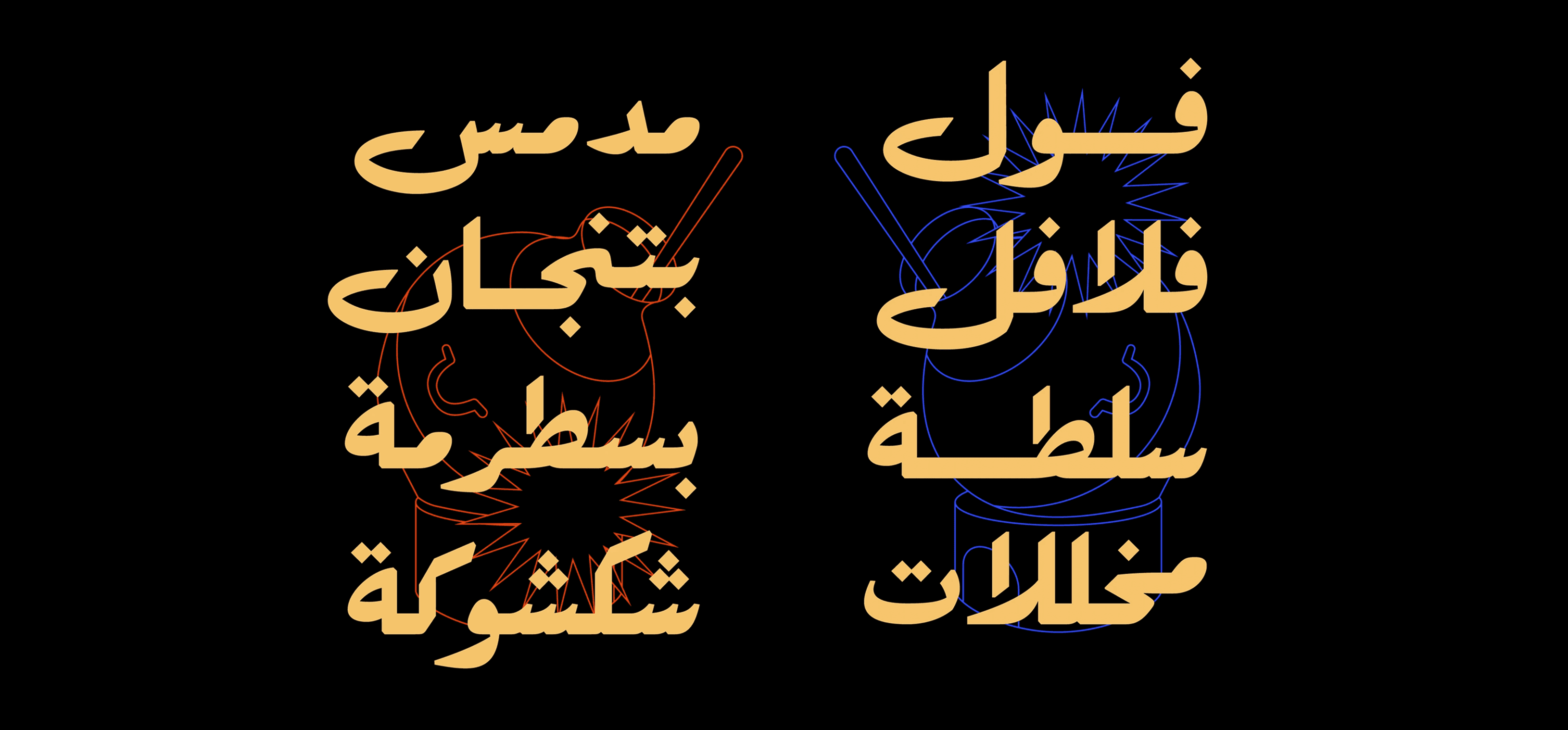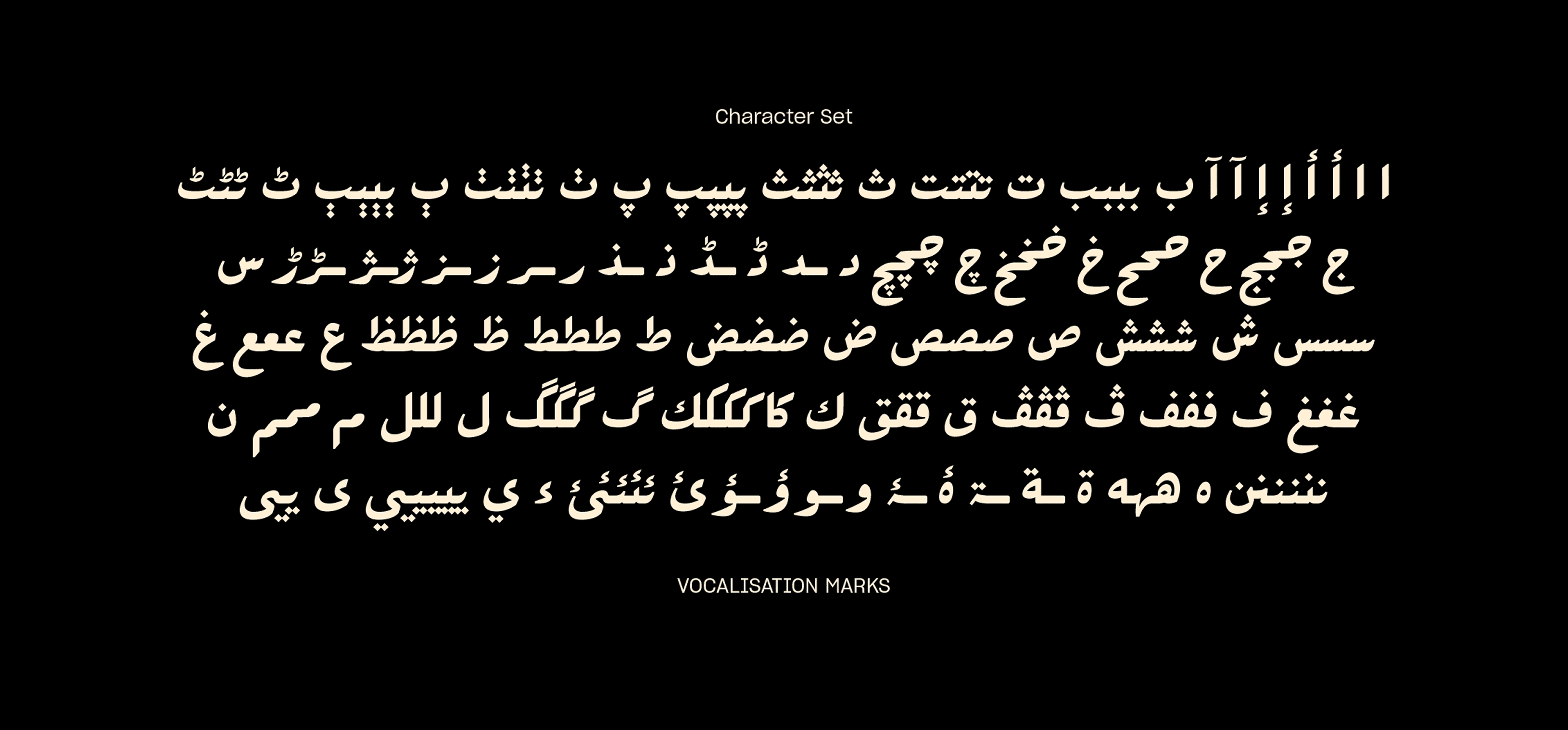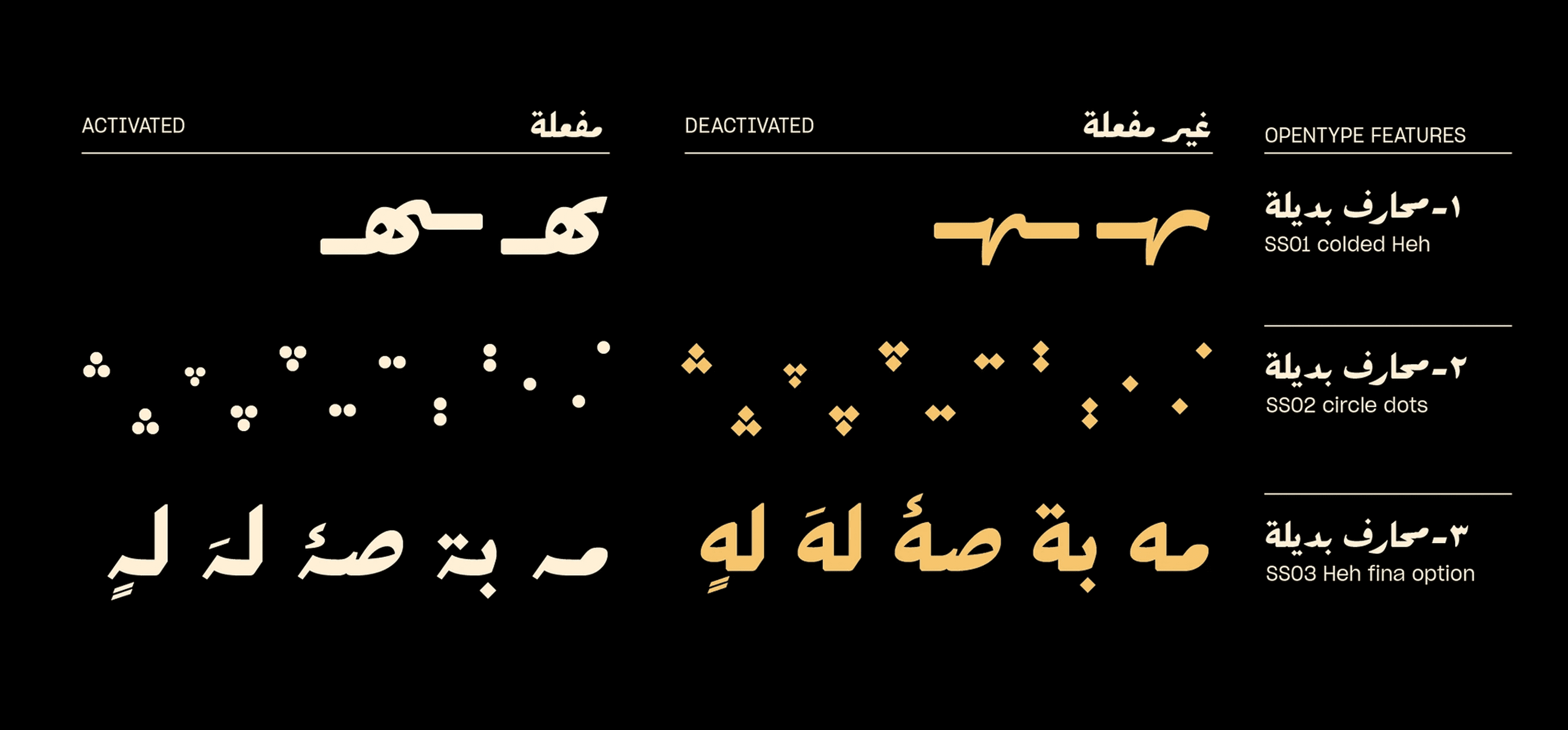
في اللغة العربية، تعني كلمة "فلفل" pepper، وتعني "بهارات" spice.
تصميم الخط يشبه الطهي؛ فهو رحلة مستمرة وعمل دائم التطور.
ويُعد فلفل أول عضو في عائلة قادمة من "المكونات"، يتميّز كل منها بطابع فريد، ووزن خاص، ونكهة مميزة تضيف التتبيلة المثالية لأي مشروع تصميمي.